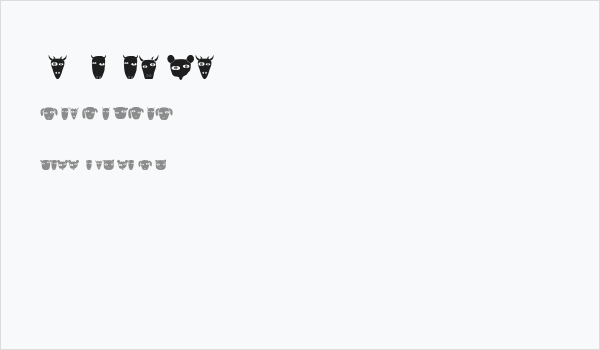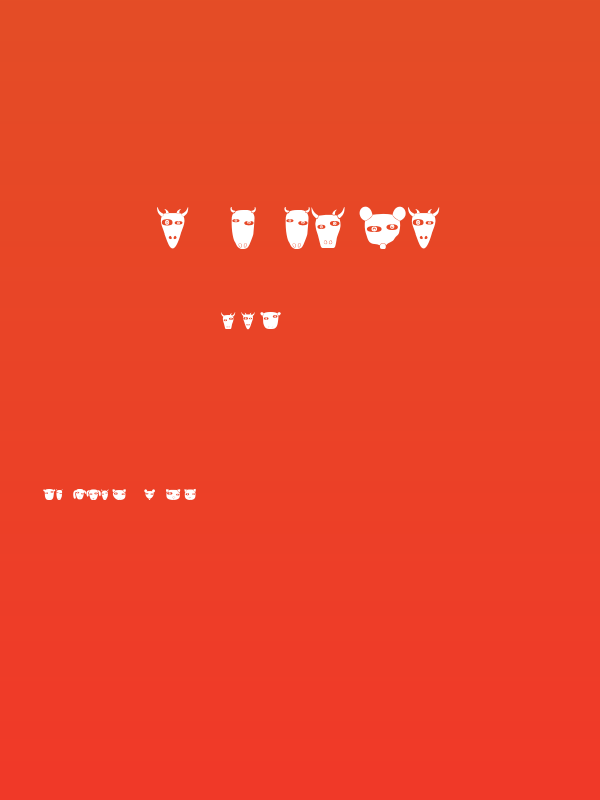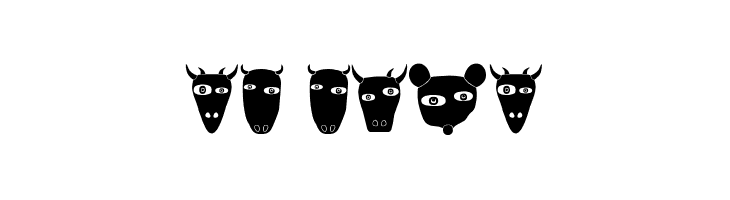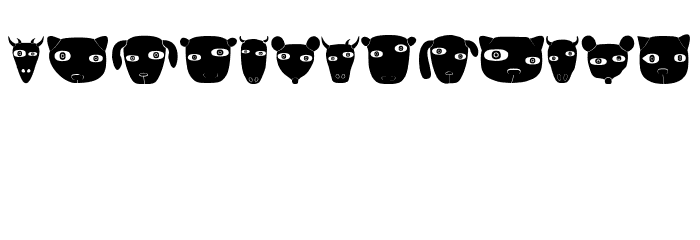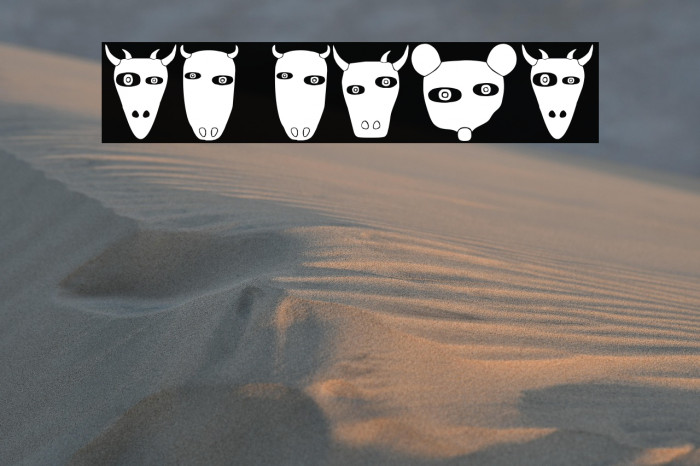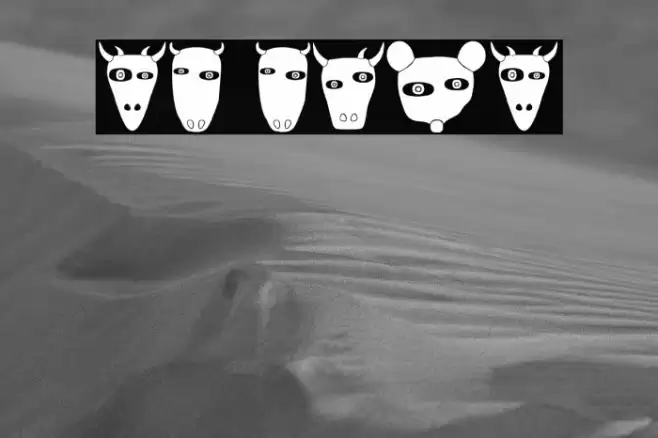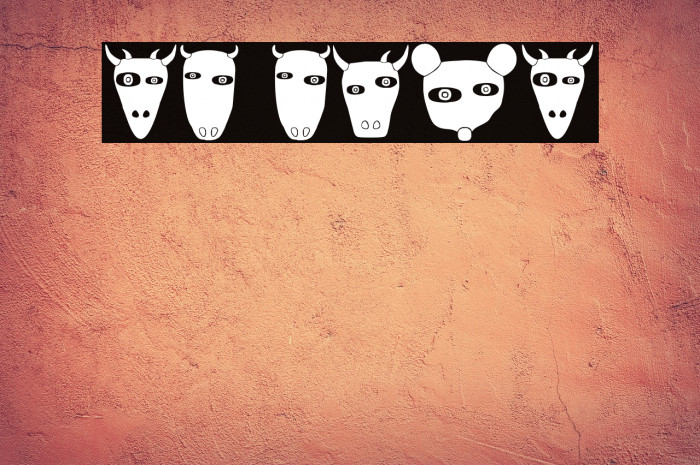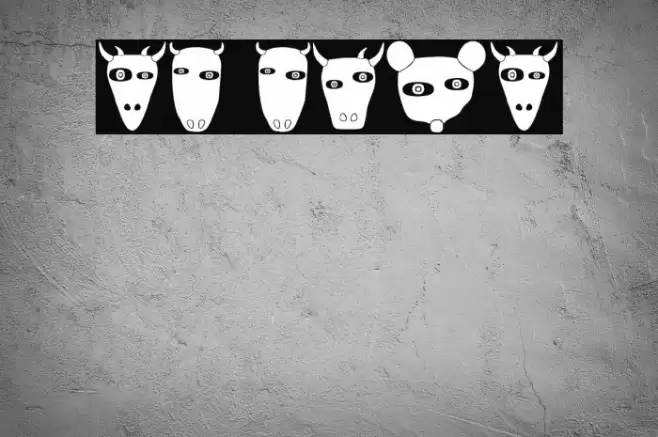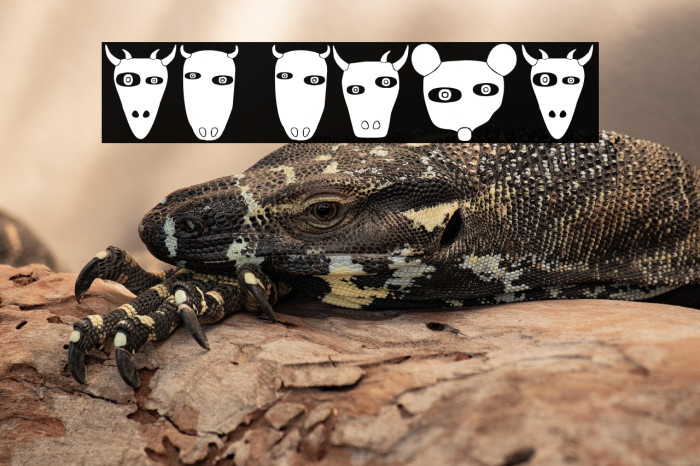
Nature Regular Font
| Caso d'uso | Logos, Posters, Children's materials |
| Progetti proposti | Ideal for children's books, playful branding, educational materials, and creative design projects. |